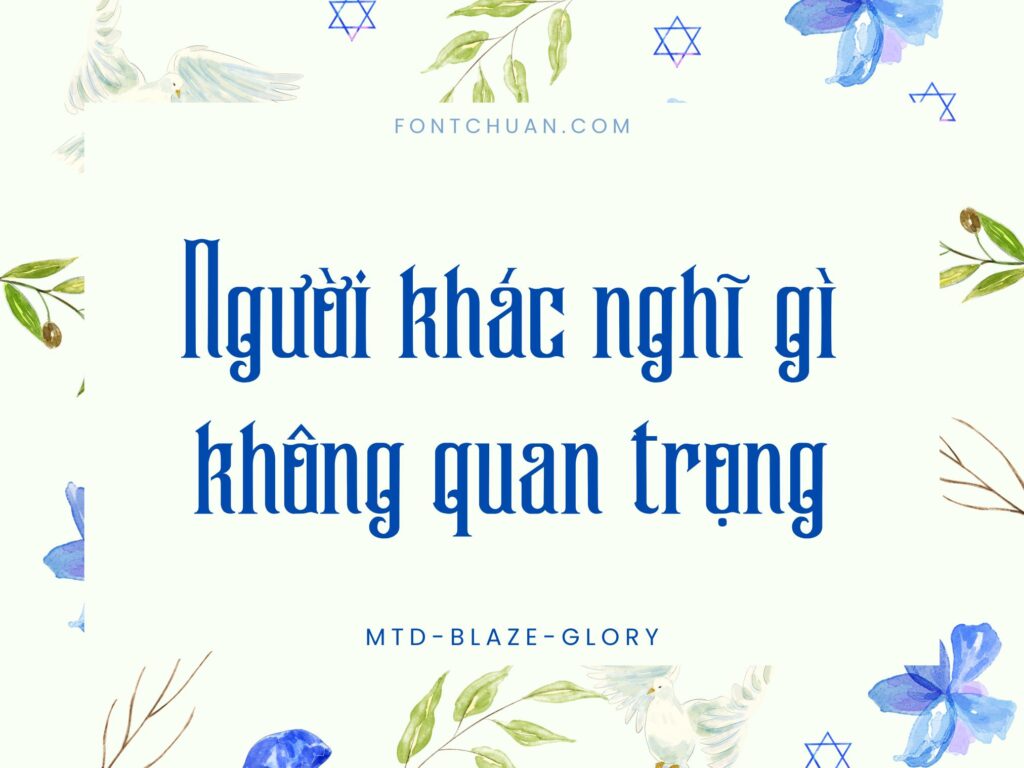
Font MTD Blaze Glory Việt Hóa
Blaze Glory là một font chữ mang phong cách mạnh mẽ và đầy sáng tạo, với các đường nét sắc sảo và độ dày nổi bật. Thiết kế của font này mang đến cảm giác năng động, thích hợp cho những dự án cần sự thu hút và nổi bật. Để hỗ trợ cộng đồng thiết kế Việt Nam, Mộc Hạ đã Việt hóa font Blaze Glory, giúp font này hỗ trợ đầy đủ tiếng Việt cùng hơn 200 ngôn ngữ khác. Phiên bản Blaze Glory Việt hóa đã được thành viên Font Chuẩn sưu tầm và đăng tải, nhằm mang đến sự lựa chọn phong phú hơn cho các nhà thiết kế.
Về đặc điểm thiết kế, Blaze Glory sở hữu các ký tự có cấu trúc vững chắc, mang đến cảm giác khỏe khoắn và hiện đại. Font này rất phù hợp cho các thiết kế tiêu đề lớn, poster quảng cáo, logo thương hiệu và các sản phẩm đồ họa cần sự táo bạo. Ngoài ra, Blaze Glory cũng là một lựa chọn lý tưởng cho các ngành nghề như quảng cáo, công nghệ và giáo dục, mang đến phong cách mạnh mẽ và chuyên nghiệp. Font này cũng rất thích hợp cho các sự kiện như Halloween, Lễ hội và các dịp đặc biệt khác.
Bên cạnh đó, Blaze Glory cũng được ứng dụng như một Font chữ Halloween mang phong cách mạnh mẽ, góc cạnh và đậm chất sáng tạo. Với những đường nét sắc sảo cùng độ dày nổi bật, font này tạo cảm giác táo bạo và năng động, rất phù hợp cho các thiết kế chủ đề lễ hội hoặc sự kiện cần sự cuốn hút. Không chỉ dành cho các ấn phẩm Halloween, Blaze Glory còn được ứng dụng rộng rãi trong thiết kế poster, logo thương hiệu, tiêu đề quảng cáo và đồ họa công nghệ. Phiên bản Blaze Glory Việt hóa do Mộc Hạ thực hiện giúp font hỗ trợ tiếng Việt hoàn chỉnh, mở rộng khả năng sử dụng cho cộng đồng thiết kế Việt Nam và quốc tế.